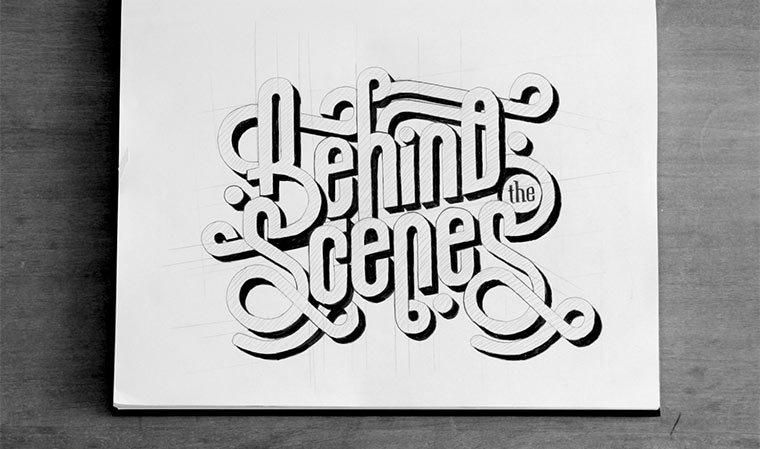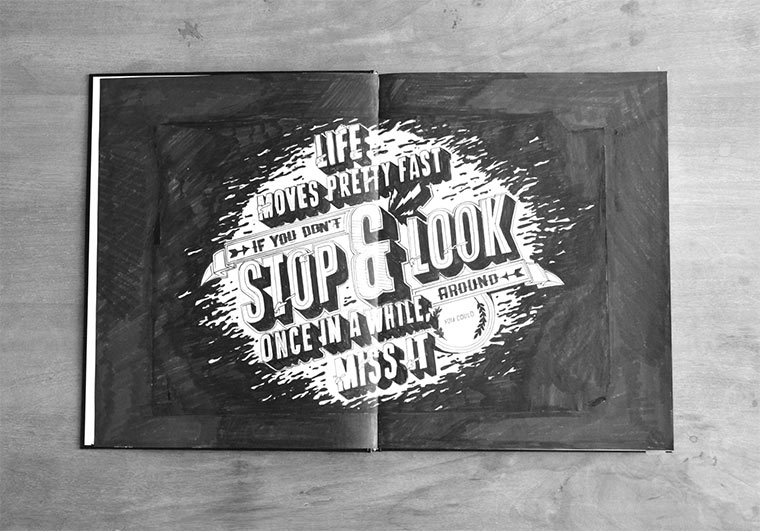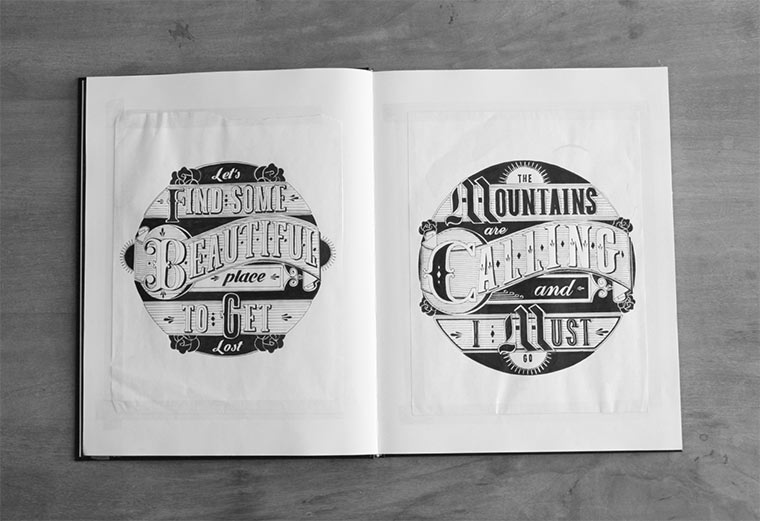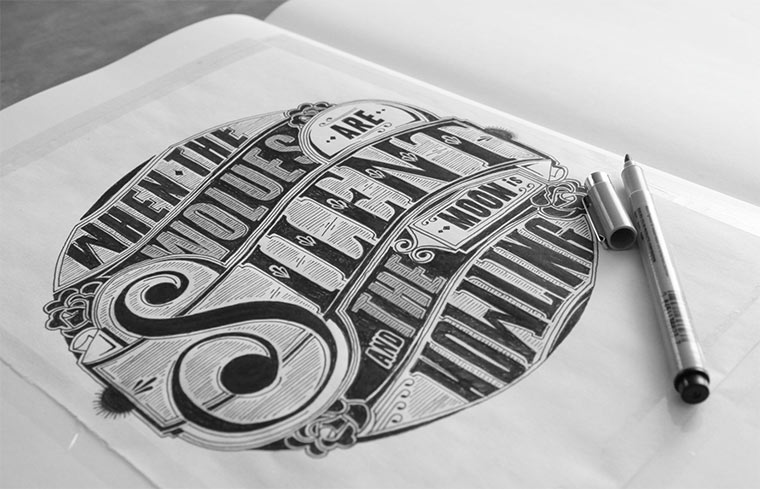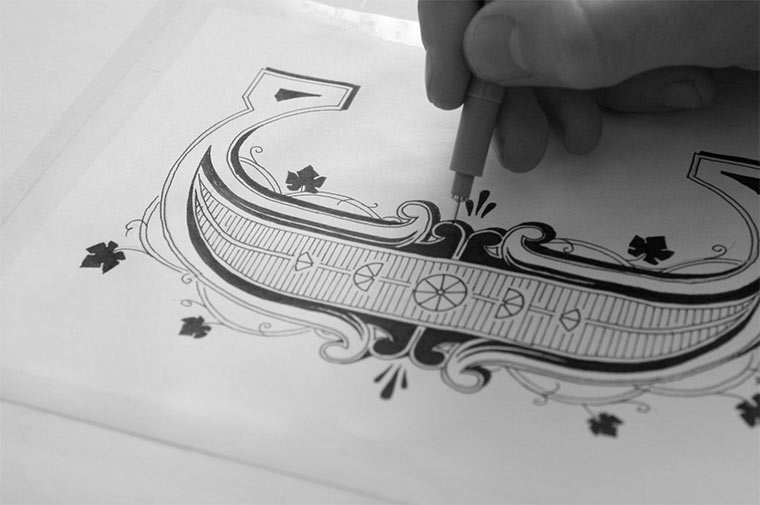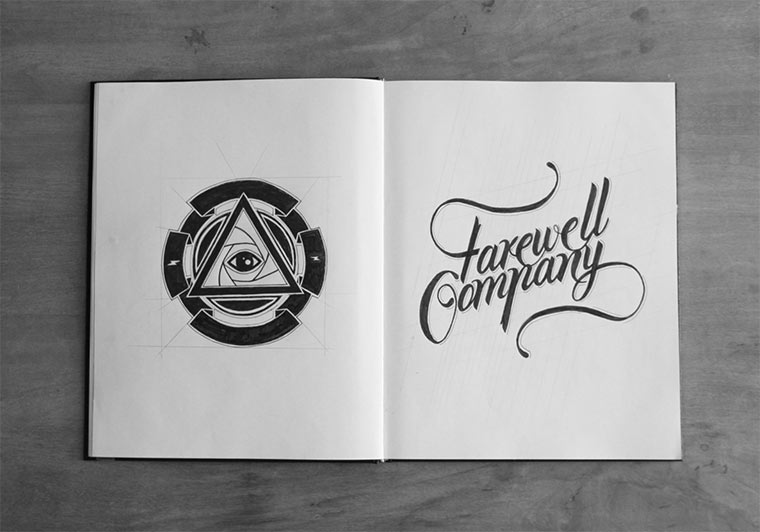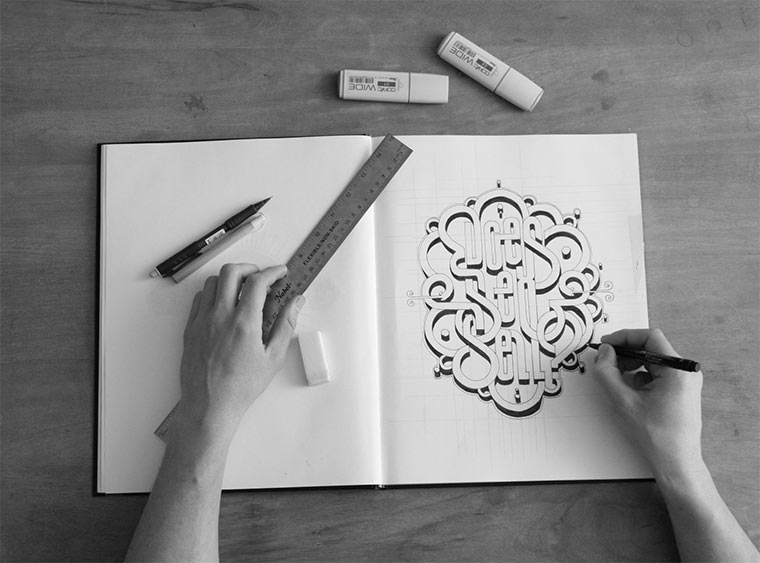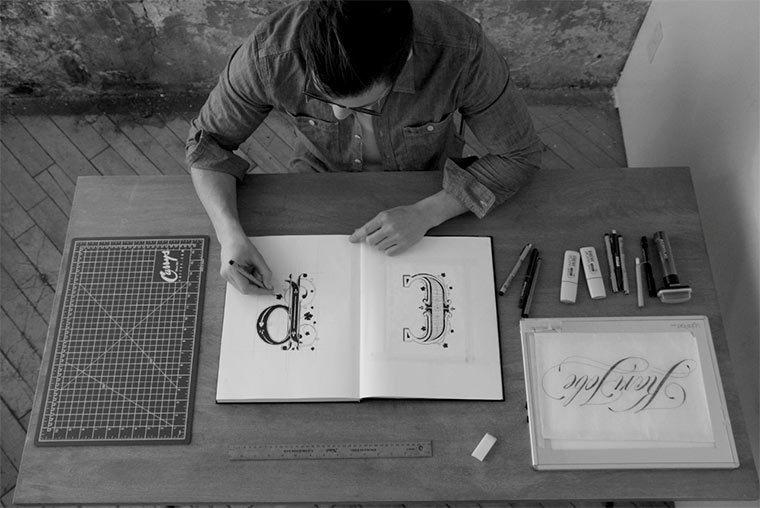
Ein ganzes Notizbuch voll
Typografie-Zeichnungen von Ben Johnston
Der Kanadier Ben Johnston betreibt Hand Lettering, also das akkurate Zeichnen von Buchstaben. Die hohe Kunst liegt darin, die Buchstaben möglichst gedruckt aussehen zu lassen. Wirft man einen Blick in das vollgezeichnete Notizbuch von Johnston, merkt man schnell, dass er genau das drauf hat.